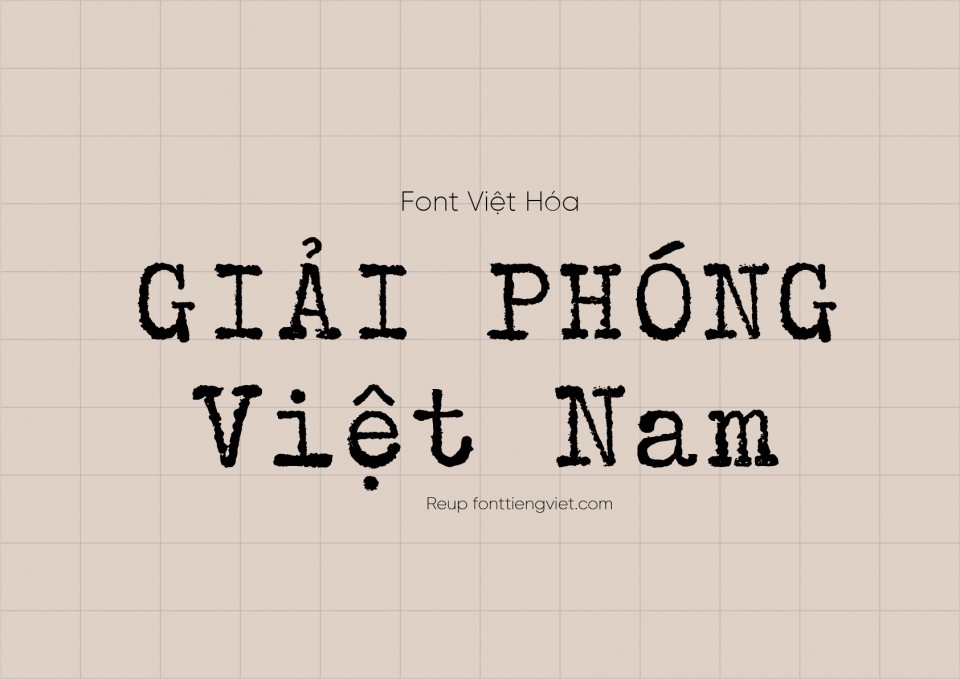
Font việt hóa VL Typewriter BasiX (2 font)
Bạn đang tìm kiếm một bộ Font Miễn Phí mang phong cách máy đánh chữ truyền thống để làm mới các thiết kế của mình? Font việt hóa VL Typewriter BasiX (2 font) chính là sự lựa chọn hoàn hảo dành cho cộng đồng yêu đồ họa tại Việt Nam. Với thiết kế mô phỏng chân thực từng nét gõ trên giấy, bộ font này không chỉ mang lại cảm giác hoài cổ mà còn giúp nội dung truyền tải trở nên gần gũi và mộc mạc hơn. Việc sử dụng các font chữ đã được việt hóa giúp người dùng dễ dàng thể hiện đầy đủ các ký tự tiếng Việt có dấu mà không lo bị lỗi hiển thị.
Đặc điểm nổi bật của Font việt hóa VL Typewriter BasiX (2 font)
Thiết kế đậm chất Retro và ứng dụng đa dạng
Bộ Font việt hóa VL Typewriter BasiX (2 font) bao gồm hai biến thể khác nhau, cung cấp sự linh hoạt tối đa cho người sử dụng. Font chữ này tái hiện hoàn hảo các vết mực không đều và cấu trúc thô sơ đặc trưng của máy đánh chữ xưa. Trong môi trường học đường, các bạn học sinh và giáo viên có thể dùng nó để trang trí báo tường, làm bìa tiểu luận hoặc thiết kế các poster mang hơi hướng vintage. Đây là công cụ đắc lực giúp tạo điểm nhấn khác biệt so với các font chữ hiện đại thông thường.
Tối ưu hóa cho người dùng Việt Nam
Điểm mạnh nhất của bộ font này là khả năng tương thích cao với các bộ gõ phổ biến như Unikey hay VietKey. Mọi dấu câu và ký tự đặc biệt đều được căn chỉnh tỉ mỉ, đảm bảo tính thẩm mỹ đồng nhất trên toàn văn bản. Dù bạn đang làm việc trên các phần mềm thiết kế chuyên nghiệp hay chỉ đơn giản là soạn thảo văn bản, bộ font vẫn giữ được độ sắc nét và chuyên nghiệp cần thiết.
Kết luận và trải nghiệm Font việt hóa VL Typewriter BasiX (2 font)